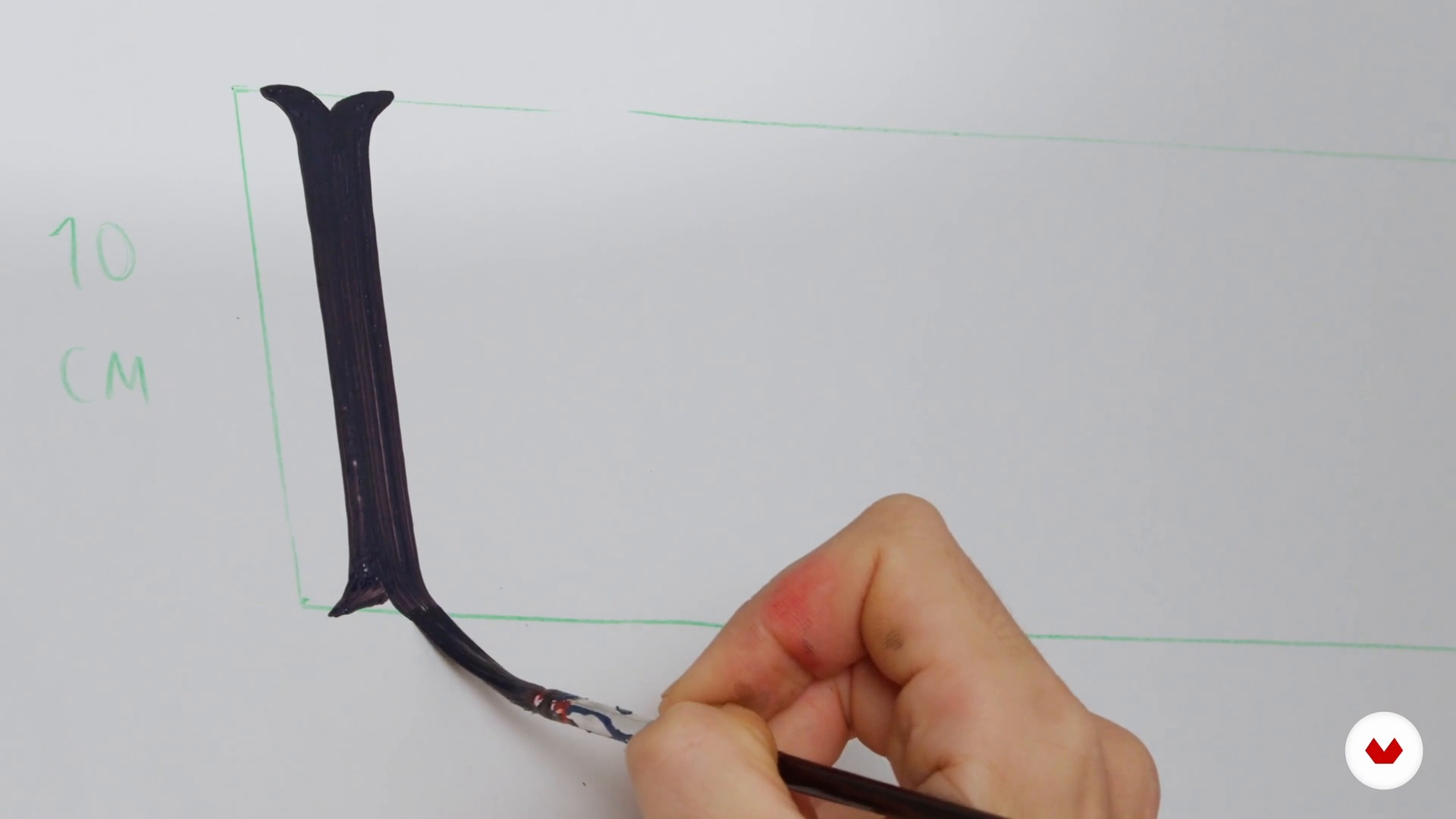
Populäres brasilianisches Lettering
Andere Schriftarten
Über die Videolektion: Andere Schriftarten
“Da Sie bereits wissen, wie man Buchstaben malt, lernen Sie nun weitere Alphabetstile kennen, die auch in Ihrem Kursprojekt verwendet werden können.”
In dieser Videolektion behandelt Filipe Grimaldi das Thema: Andere Schriftarten, das Teil dieses Domestika-Onlinekurses ist: Populäres brasilianisches Lettering. Bringe deine Designfähigkeiten mit populärem brasilianischen Lettering auf die nächste Stufe. Meistere die Kunst von Pinsel und Farbe, um authentische Buchstaben und Symbole zu gestalten..
Partielle Transkription des Videos
“Nachdem wir nun den Pinsel des Lyrikers beherrschen, In dieser Klasse treffen wir drei neue Alphabete, die vom Pinsel selbst generiert werden, Keine Konstruktionszeichnung erforderlich. Die drei Alphabete, die wir jetzt kennen werden, waren Alphabete, die ich kartiert habe für meine Forschung in Brasilien und Lateinamerika. Ich habe diese drei Alphabete zugeordnet, weil ich das Bedürfnis verspürte, die 24 Buchstaben und Zahlen zu haben, damit sie von mir und anderen Textern nachgebildet werden können. Bei diesen Alphabeten handelt es sich um manuelle Arbeiten, die von Hand zu Hand variieren...”